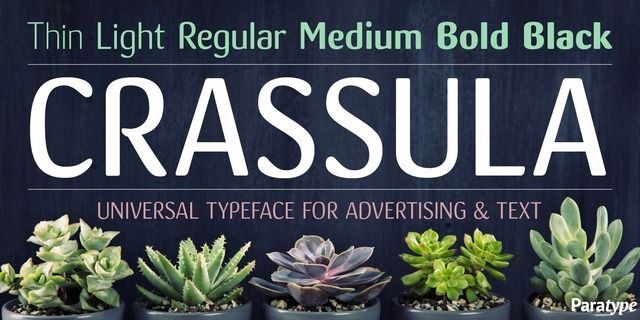
Crassula — универсальный акцидентный шрифт. Как и одноимённое растение (крассула, толстянка, «денежное дерево»), имеющее округлые сочные листья, шрифт отличается округлыми контурами и сглаженными формами элементов. За счёт дополнительного стилистического набора знаков, содержащего варианты букв, более близкие к традиционным, Crassula хорошо читается не только в коротких, но и в длинных текстах. Шесть вариантов по насыщенности расширяют возможности использования в неформальных заголовках книг и журналов, а также в доверительной рекламе. Шрифт подготовлен дизайнером Натальей Васильевой и выпущен компанией ПараТайп в 2018 году.
Функции начертания Crassula BlackПрименение в макете:
Ассоциации c начертанием Crassula BlackКачества и характер:
мягкий, приятный, уютный, комфортный, дружелюбный, добрый, оптимистичный, сочный, милый, летний, семейный, домашний, вкусный, свежий, оригинальный, самобытный, пластичный, гибкий, гладкий, качественный, аккуратный, игривый, яркий, выразительный, заметный, броский, мотивирующий, сильный, забавный, прикольный, доброжелательный, приветливый, мультяшный, живой, рукотворный, радостный, честный, здоровый, позитивный, ручной, понятный, тяжелый, толстый, детский, активный, щедрый, праздничный, аппетитный, статичный, натуральный, природный, резиновый, обильный, изобильный, насыщенный
еда, кафе, закуска, сок, фломастеры, здоровье, краска, природа, булочная, лето, отдых, семья, хенд мейд, развлечения, игра, магазин, торговля, игрушка, детская книжка, мультфильм, праздник, десерт, конфеты, кондитерская, сладости, мороженное, анимация, пластилин, молоко, маффин, выставка, канцтовары, пицца, украшение, селфи, фаст фуд, выпечка, кондитер, подарки, шоу, телевидение, смузи, соус, сметана, кетчуп, чипсы, сыр Стилистика: